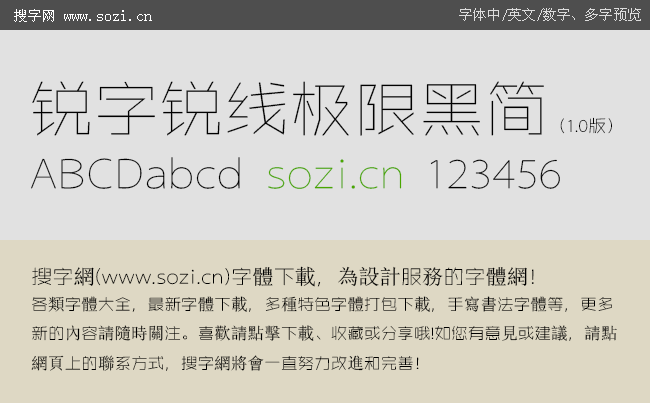
銳字銳線極限黑簡
搜字網(wǎng)提供一款銳字銳線極限黑簡中文字體下載,銳字銳線極限黑簡是一款以線體為原形設(shè)計的中文藝術(shù)字體,字體簡潔漂亮,效果非常出色,GBK編碼收字更全,適合應(yīng)用于廣告設(shè)計、名片設(shè)計、包裝印刷、產(chǎn)品設(shè)計等應(yīng)用。